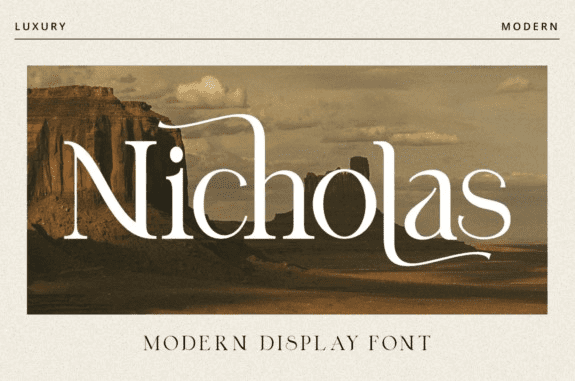
Название: Nicholas Font
Nicholas - это простой и непринужденный шрифт с засечками, бесспорно чистый.
Благодаря аккуратному и красивому расположению букв этот шрифт будет выглядеть выдающимся как в формальном, так и в неформальном дизайне.